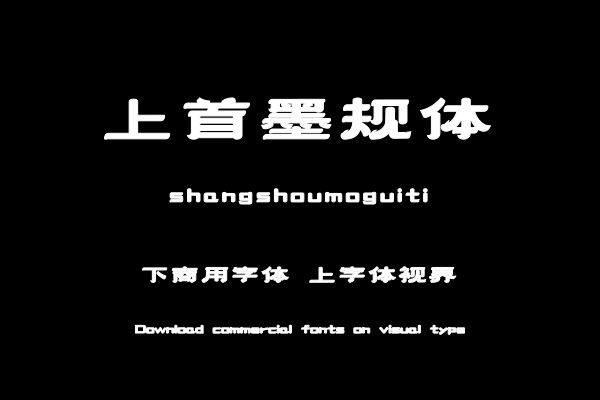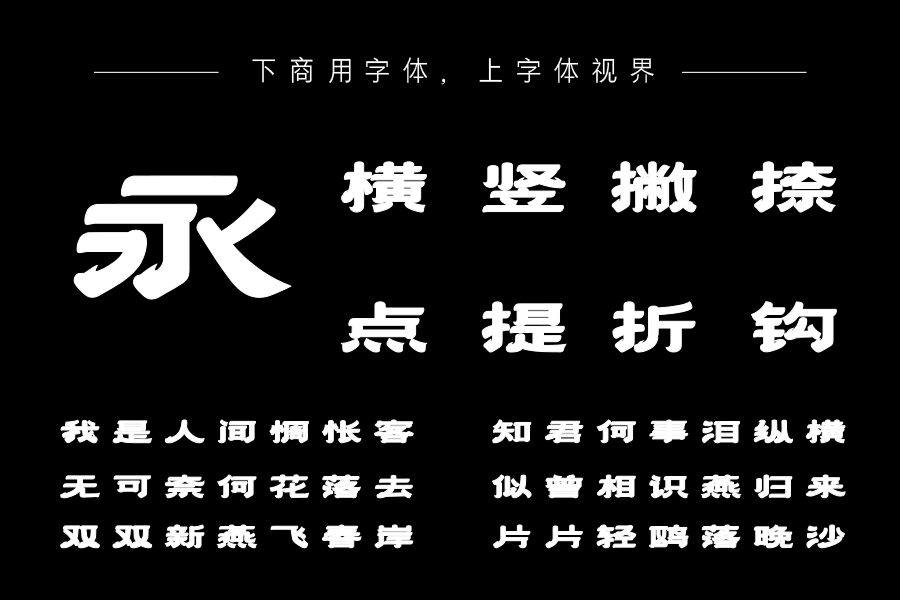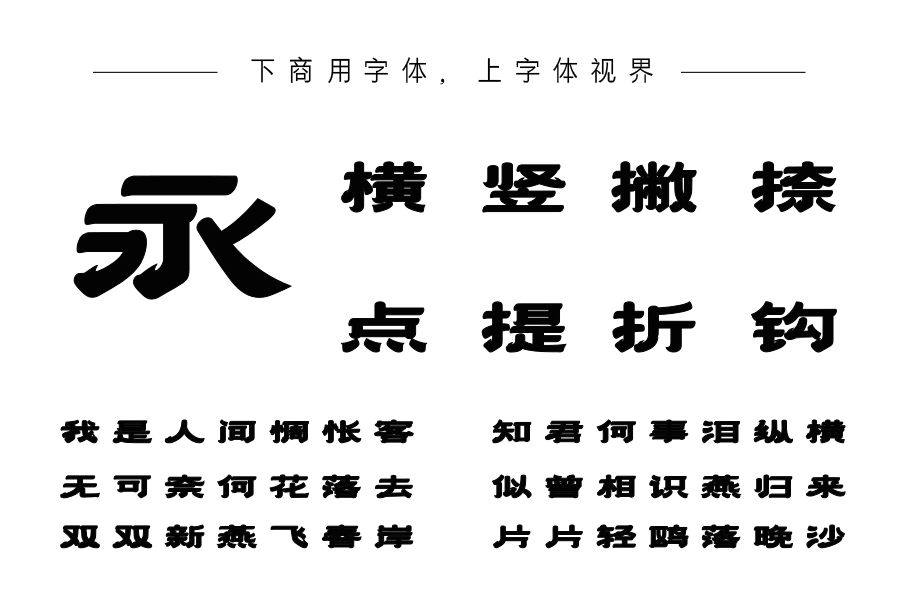
上首墨规体是一款融合了传统书法艺术与现代设计美学的独特字体。它的笔画充满了毛笔字的笔锋韵味,流畅潇洒,仿佛带着浓厚的墨香气息,展现出中国书法特有的灵动与力量感。购买须知:“下载服务费”与“字体VIP”所获得字体 仅用于个人非商用, 商用请联系付费授权。本字体为电脑用字,手机没有root权限不支持直接手机换字(手机如何root,请自行百度搜索教程)。购买前请先 了解清楚后再付款 ,字体为虚拟产品无法回收 一旦购买不支持退款。